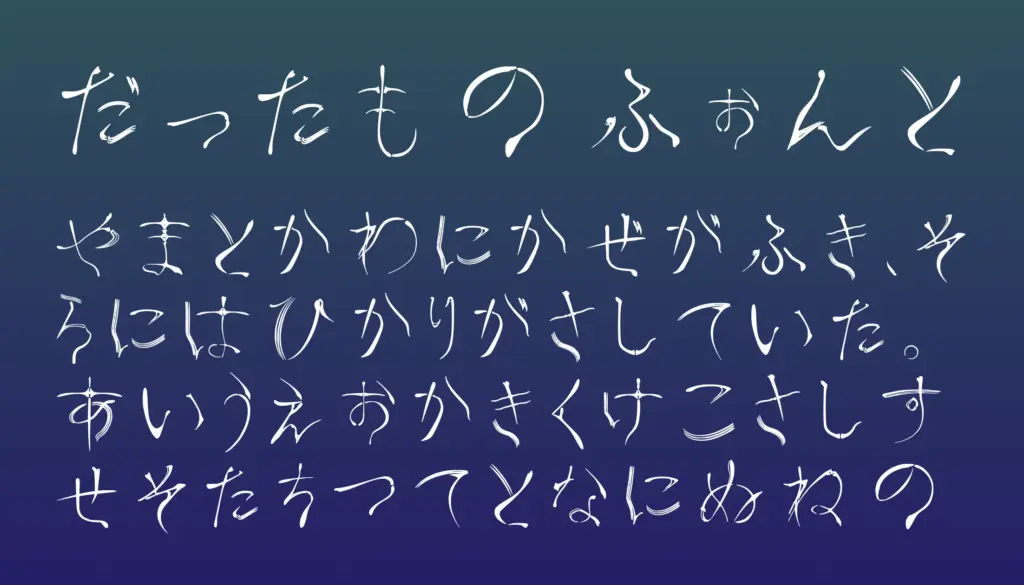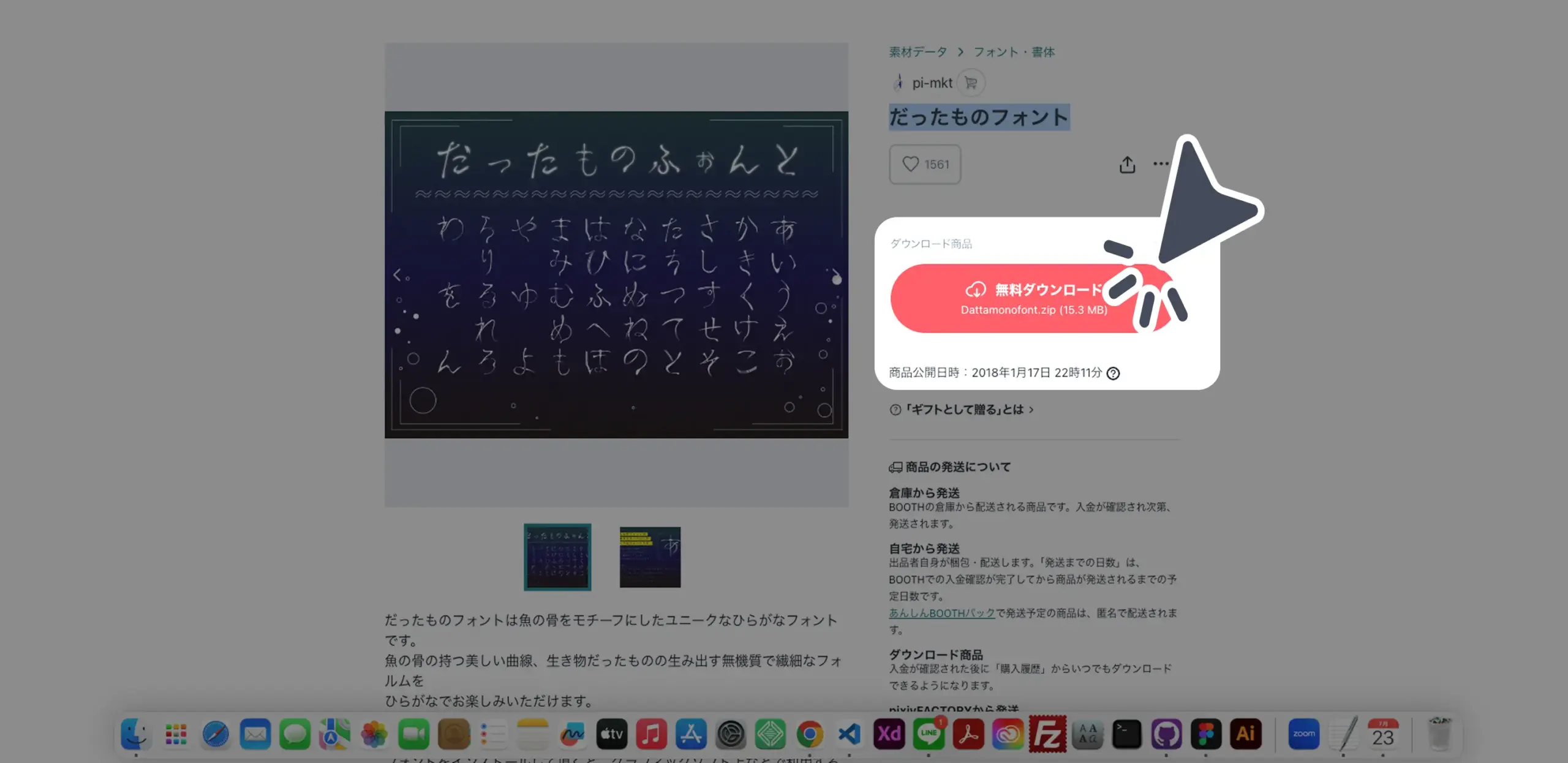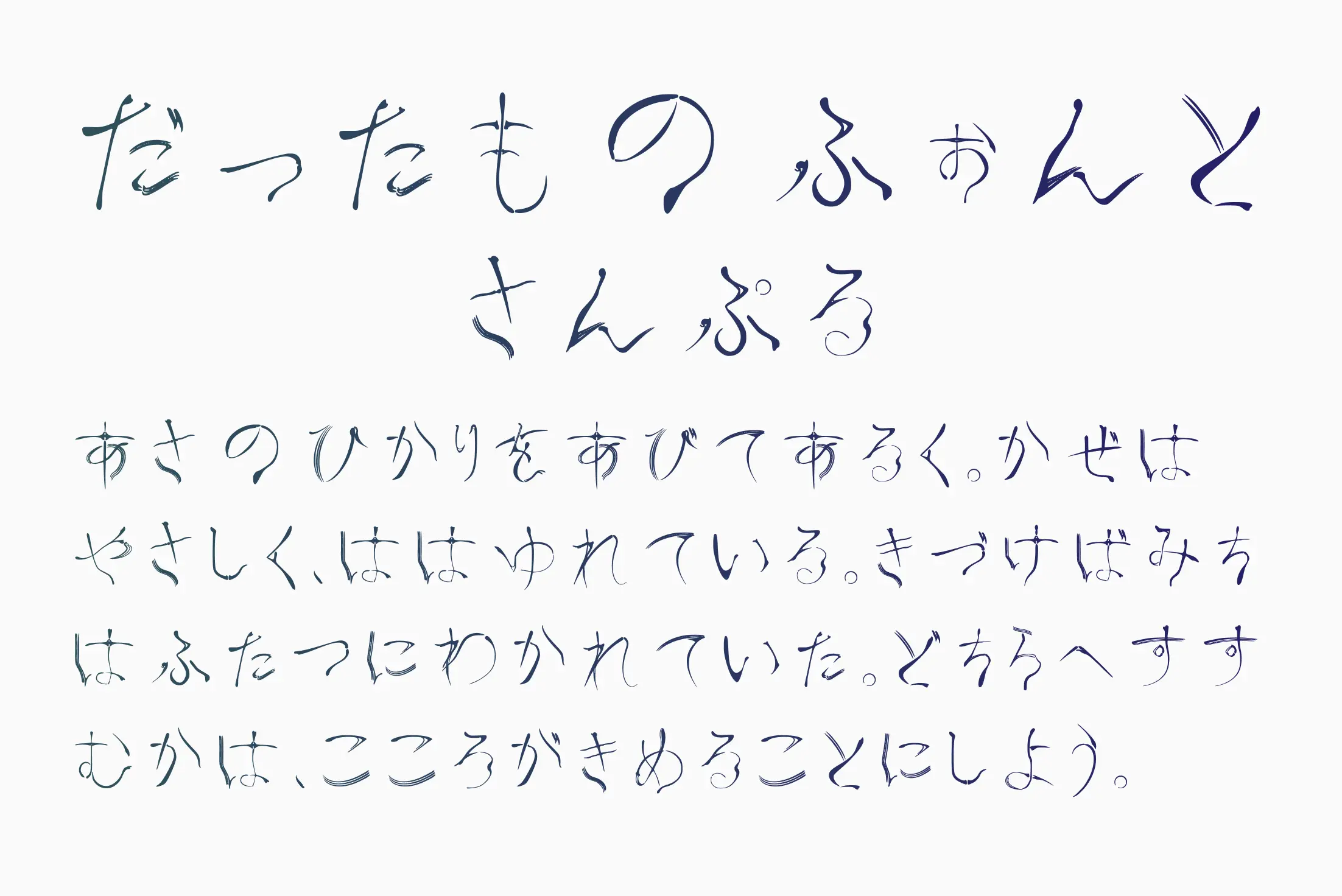
壊れかけた文字のような独特のデザインが特徴の日本語フリーフォントです。文字が一部欠けたり、細いラインが崩れていたりと、廃墟や崩壊した世界観を連想させるアート性の高い仕上がりになっています。ホラーやサスペンス、ポストアポカリプス系の作品ロゴやバナーに最適で、視覚的なインパクトを強調したいときに効果的です。
だったものフォント